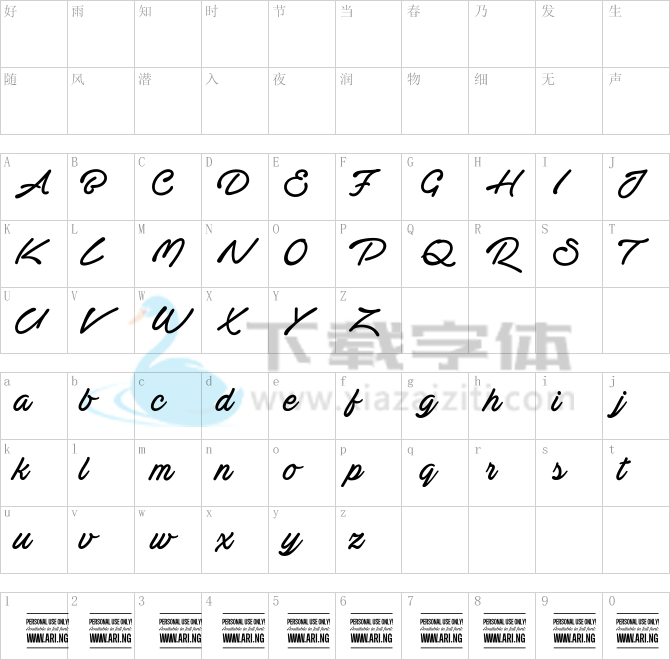
Actonia Hand PERSONAL USE.ttf字体下载,这款字体结构工整、笔画清晰,兼顾美观与易读性,适用于标题、正文、海报、包装、LOGO 等多种场景。字形优雅稳定,风格百搭耐看,适配日常排版与创意设计,让文字呈现更舒适、更具质感。Actonia Hand PERSONAL USE.ttf字体下载一笔一画,皆是细节,以均衡的比例、流畅的线条打造舒适视觉体验,字形端正大气,风格简约现代。无论是商业设计、品牌宣传还是日常排版,都能轻松驾驭,让文字更有格调与力量。Actonia Hand PERSONAL USE.ttf字体下载字体下载。